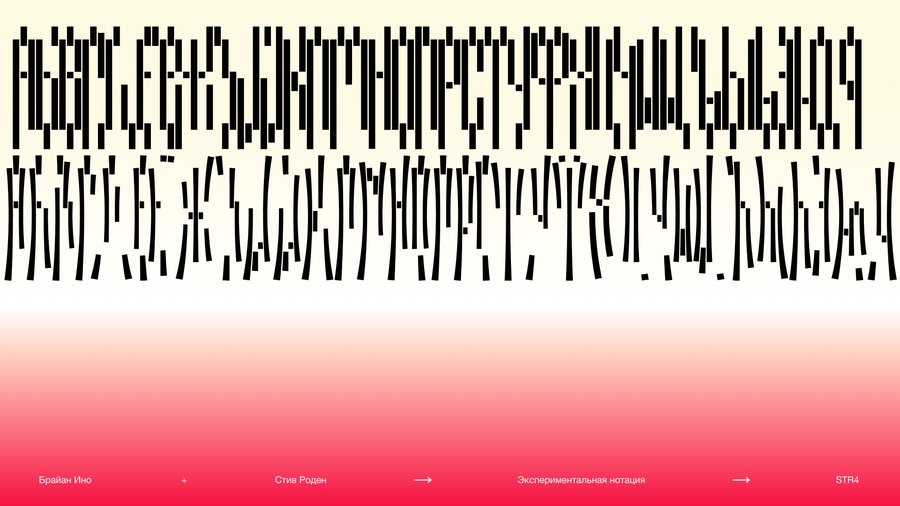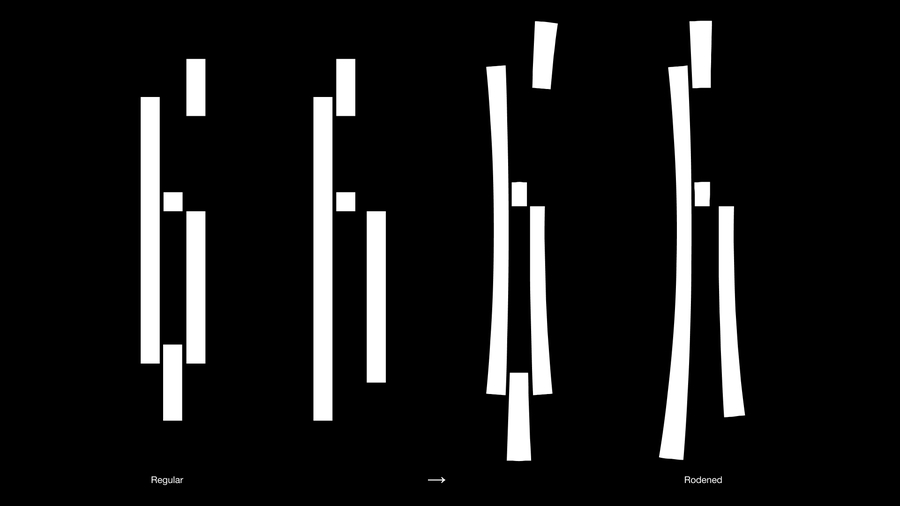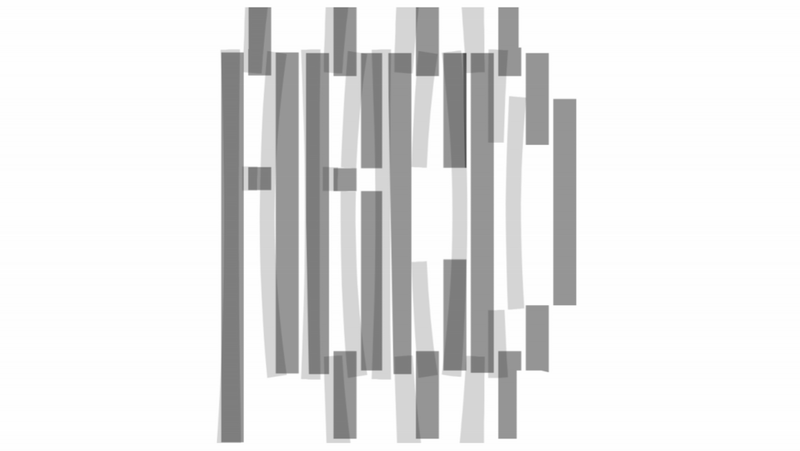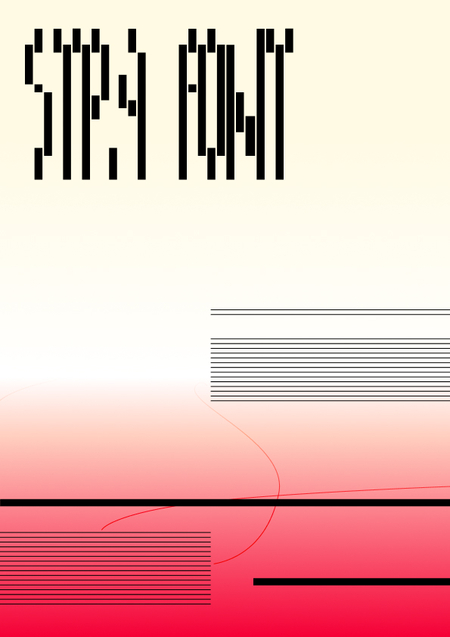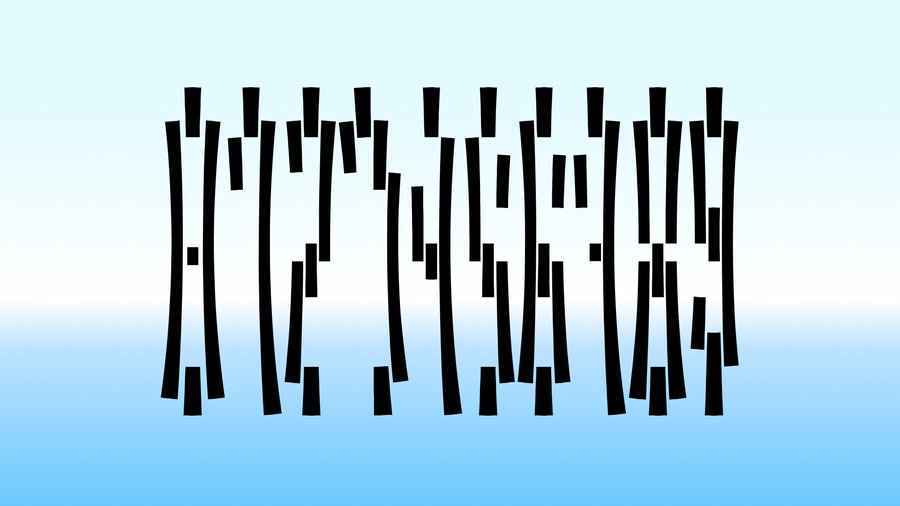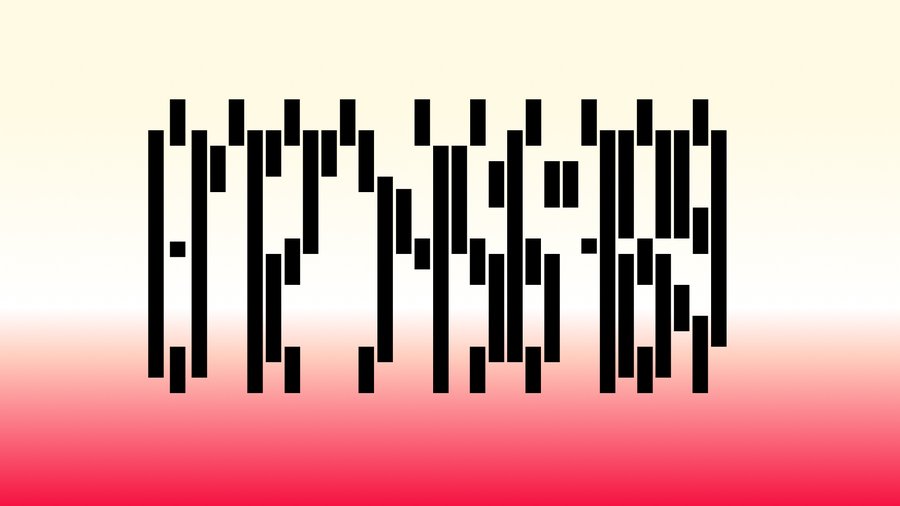
Str4 — вариативный шрифт, вдохновлённый экспериментальной нотацией.
Он соединяет два визуальных языка: модульную нотацию Брайана Ино и деформированные сетки экспрессивных партитур Стива Родена. В Str4 буква мыслится как звуковой модуль, а её деформация отражает изменение тона.